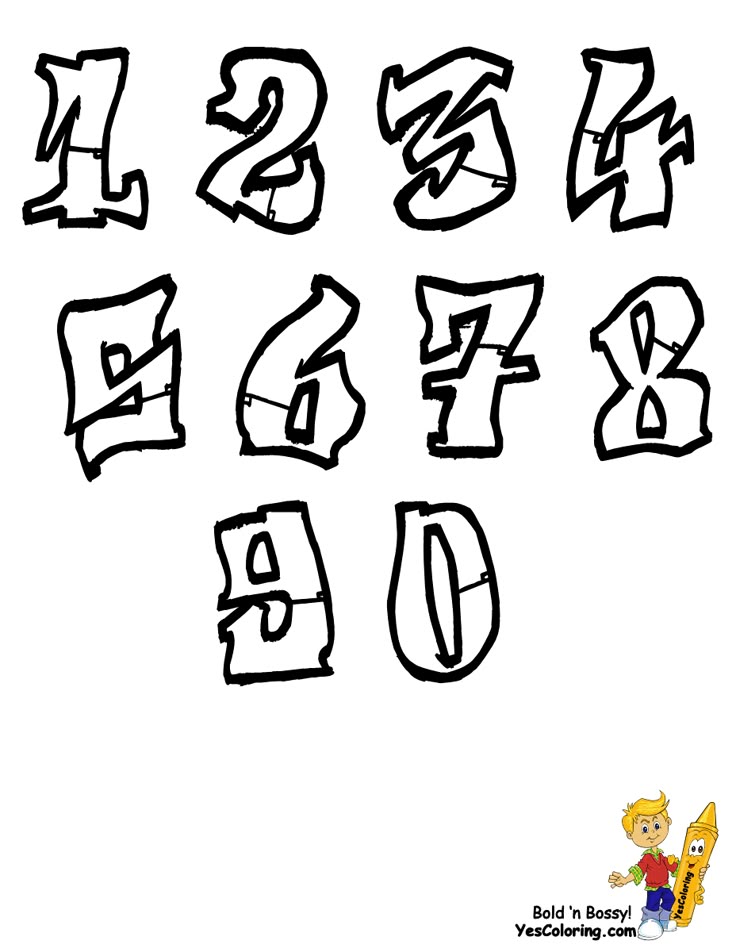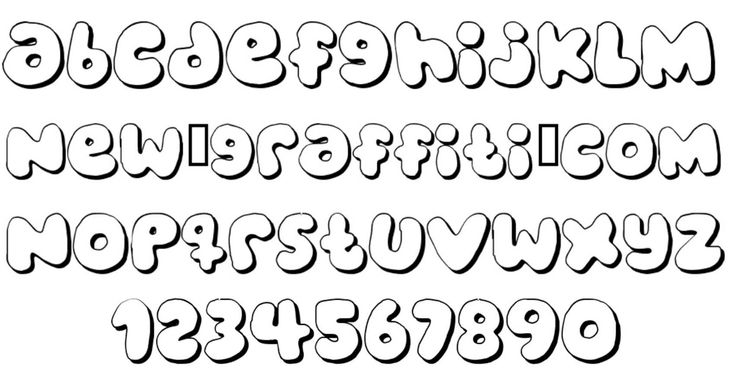
Многие райтеры имеют свой стиль и придумывают самостоятельно .
Но все равно существуют основные принципы и шрифты, которыми пользуется большинство.
Я тоже иногда придумываю свои буквы и зарисовываю их на бумаге, во-первых, чтобы не забыть, а во вторых, воспроизводить на стене знакомый шрифт потом легче, чем изобретать что-то на ходу.
Самые распространенные стили написания и буквы граффити
Баббл
Такие мультяшные объемные буквы – самый распространенный вариант. В шрифте баббл буквы должны сливаться и как бы наплывать друг на друга. Единственный минус – иногда прочитать, что написано в этом стиле довольно трудно, так как буквы могут искажаться практически до неузнаваемости.
Блокбастерс
Для этого стиля граффити нужно сначала нанести на поверхность тон. Лучше сделать это при помощи валика, но можно и баллоном. Это работа не для одного и лучше выполнять ее вместе с товарищами. На фон наносятся ровные и четкие буквы граффити. Многие райтеры используют блокбастерс как свой фирменный стиль.
Вайлд
В этом стиле буквы граффити практически невозможно прочитать. Здесь можно проявить фантазию по полной программе. Буквы можно путать, дополнять их любыми элементами и сплетать самым невообразимым образом. Вайлд – довольно сложный авторский шрифт.
20. Шрифт Bowings от Blankids
The Bowings Font — одна из самых симпатичных граффити-букв в этом списке. Это граффити в виде пузырей, которые толще вверху и тоньше внизу. Но он не теряет своего дутого вида. В этом конкретном примере буквы заполнены градиентными цветами и элементами стиля, благодаря которым верхняя часть просвечивает.